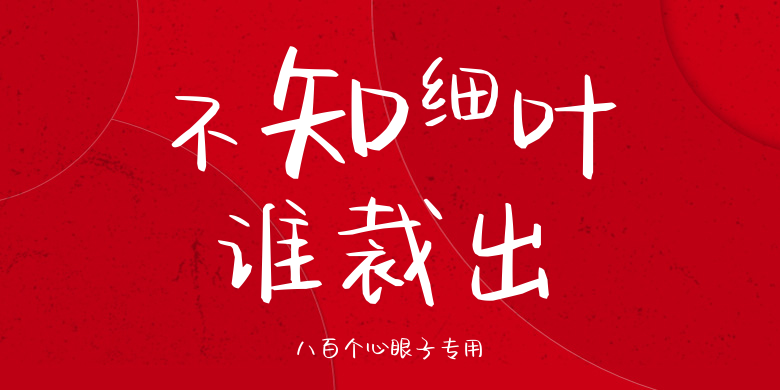
八百个心眼子专用
八百个心眼子专用,这款字体结构工整、笔画清晰,兼顾美观与易读性,适用于标题、正文、海报、包装、LOGO 等多种场景。字形优雅稳定,风格百搭耐看,适配日常排版与创意设计,让文字呈现更舒适、更具质感。八百个心眼子专用一笔一画,皆是细节,以均衡的比例、流畅的线条打造舒适视觉体验,字形端正大气,风格简约现代。无论是商业设计、品牌宣传还是日常排版,都能轻松驾驭,让文字更有格调与力量。八百个心眼子专用字体下载。